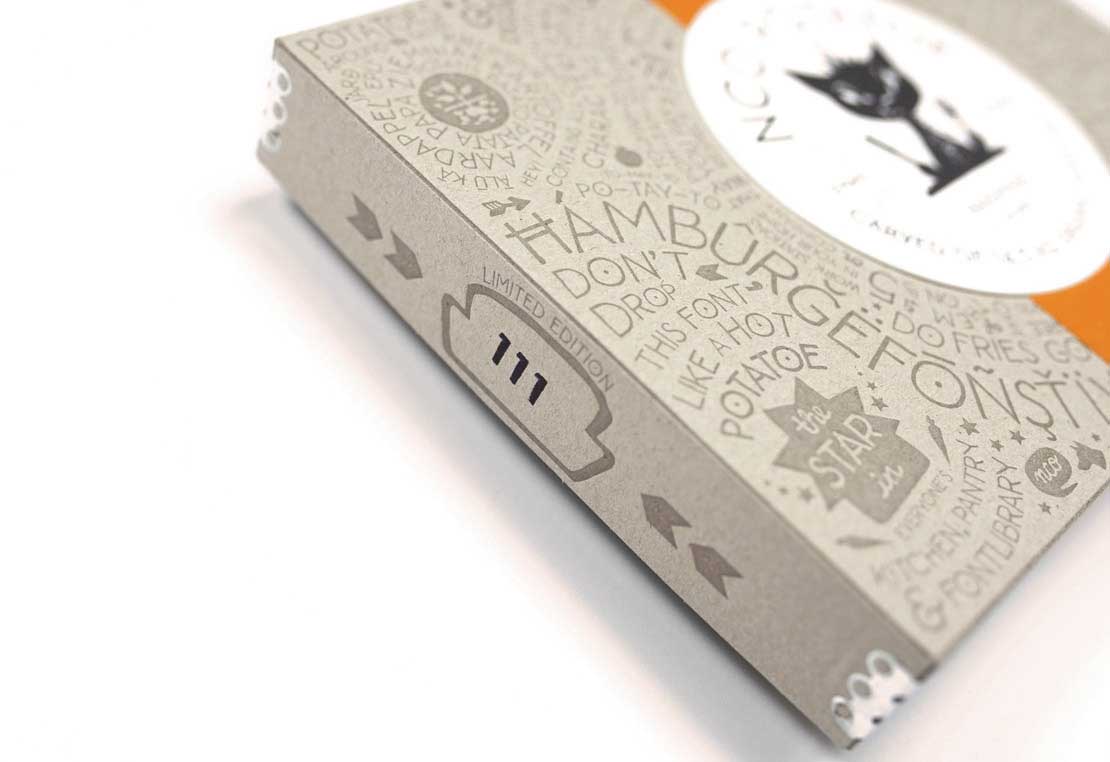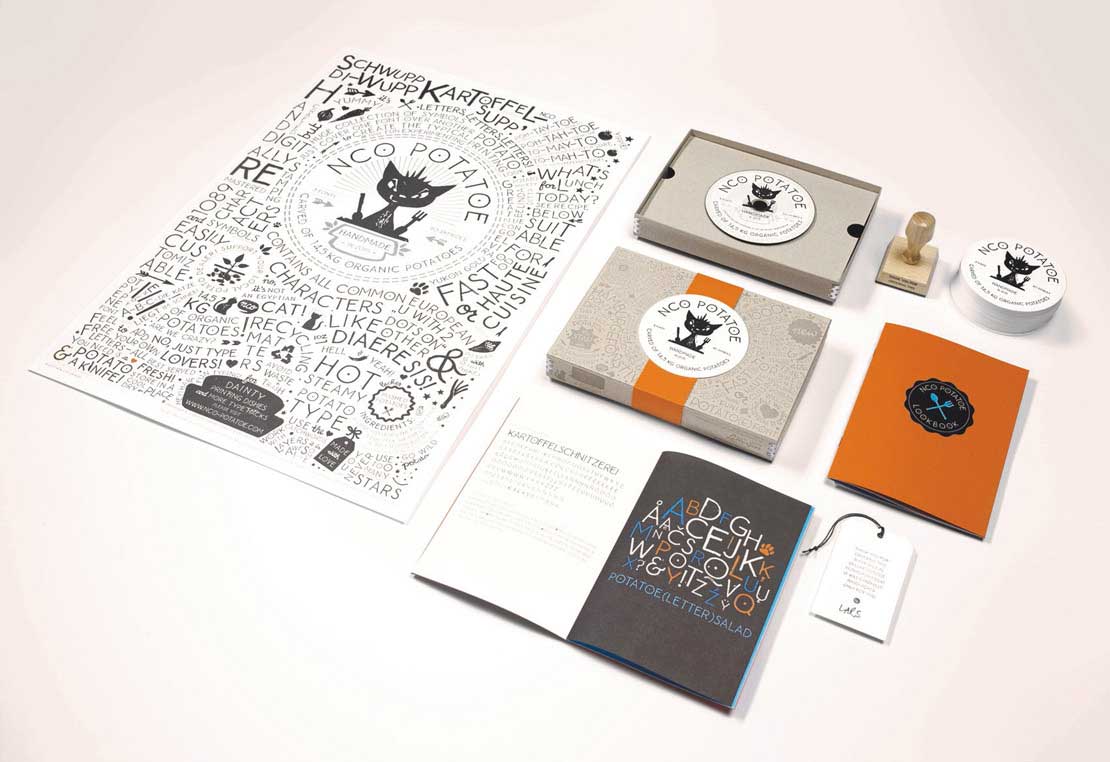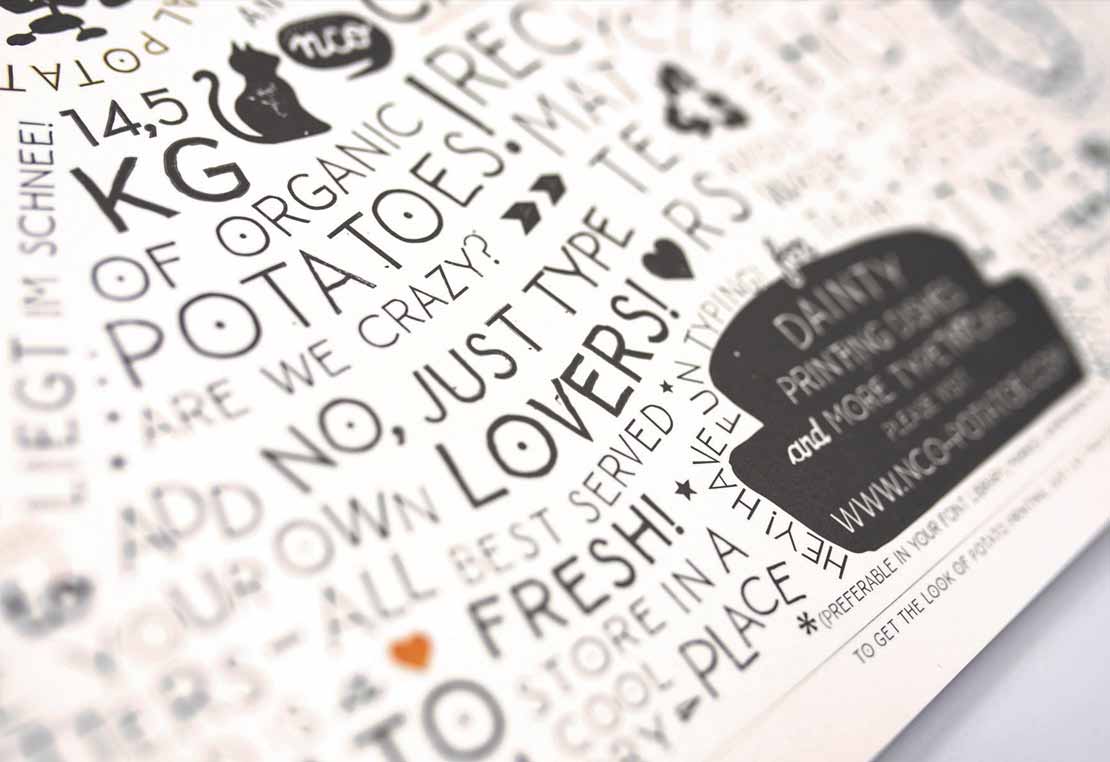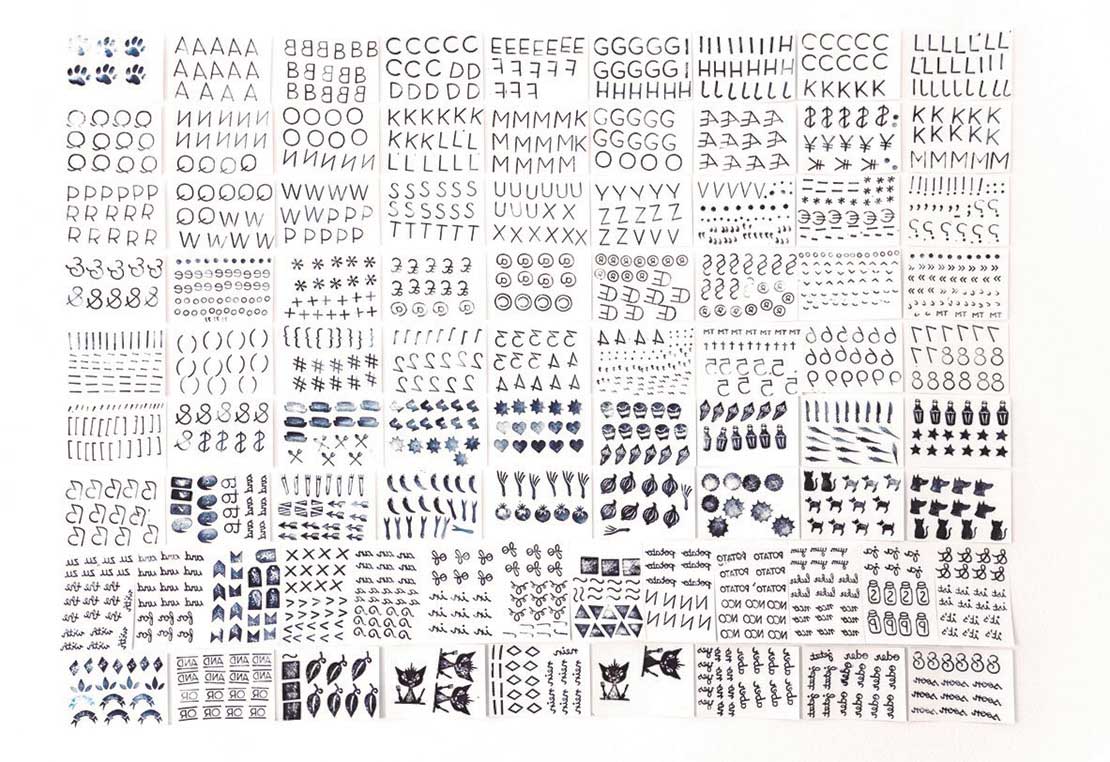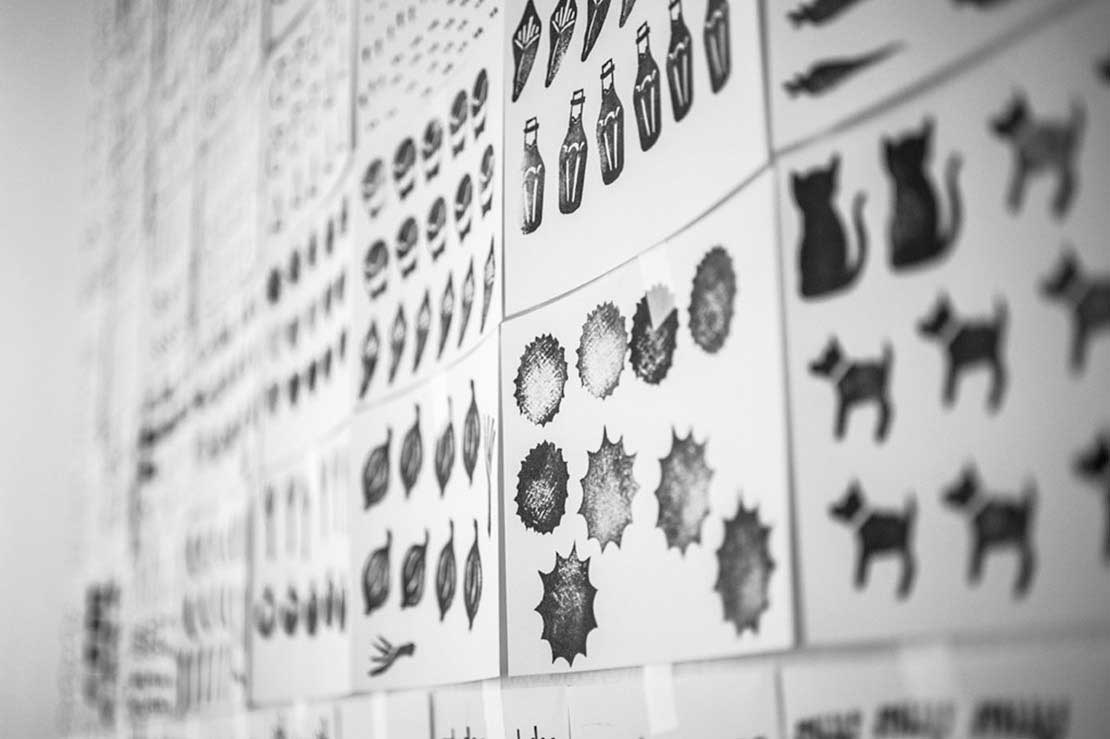
Kartoffeldruckschrift in der Box
Aus rund 14,5 kg Kartoffeln hat NEW CAT ORANGE eine handgeschnittene, digitale Kartoffeldruckschrift gestaltet. Das entstandene Schriftenset ist in einer handlichen Box erhältlich.
Kartoffeldruckschrift
Die Ursprungszeichen zu dieser Schrift sind nicht auf Papier geschibbelt oder am Computer entstanden, sondern wurden von Hand fein säuberlich aus Kartoffeln geschnitzt. Mit diesen echten Kartoffeldruckstempeln wurden die Zeichen ganz klassisch mehrfach auf Papier gedruckt, die besten ausgewählt und anschließend aufwändig digitalisiert.
»Die größte Herausforderung stellten die Quetschränder und Unsauberkeiten dar. Einerseits wollten wir eine Schrift, die auch in kleinen Schriftgraden lesbar ist, auch wenn es über zwei Zeilen hinaus geht (wenn man dies mit reinen Versalien überhaupt möchte …) andererseits sollten aber eben diese Ränder, das Auslaufen des Zeichens irgendwie erhalten bleiben. Die besten Resultate haben wir erreicht, wenn wir digital 2 Schriftschnitte übereinander legen. Also mit Layern arbeiten.«HP Becker von NEW CAT ORANGE
So besteht das Schriftenset aus der NCO-Potatoe Clean, die feine, saubere, mit den typischen, markanten Schnitzkanten, aus der NCO-Potatoe Rough, mit den typischen Löchern und Unsauberkeiten und letztendlich der NCO-Potaoe Extra. Diese eignet sich u.a. dazu, um sie „unter“ die Rough zu legen und ihr einen anderen Tonwert zuzuordnen. Auf diese Weise entstehen typische Ränder, wie man sie vom Kartoffeldruck kennt. Ergänzend dazu gibt es die NCO-Potatoe-Symbols. Hierbei handelt es sich um komplett geschnitzte Begriffe und Symbole, inspiriert aus der Imbissbudenwelt: von der Ketchupflasche bis zur Pommesgabel und diversen Pfeilen.
In Erinnerung an die gute alte (analoge) Zeit gibt es das Schriftenset in einem kleinen Kistchen. Die Kartonage aus Buchbinderpappe wurde im Buchdruck vom Druckatelier Letterjazz produziert. Sie ist banderoliert und versiegelt mit ein Bierdeckel. Innendrin findet man eine CD mit den Schriften sowie ein A2 Poster und eine 16seitige Broschüre, beides im Offset gedruckt sowie einen weiteren Bierdeckel. Bis auf das Logo wurde alles mit den Mitteln der Schrift gestaltet und illustriert.